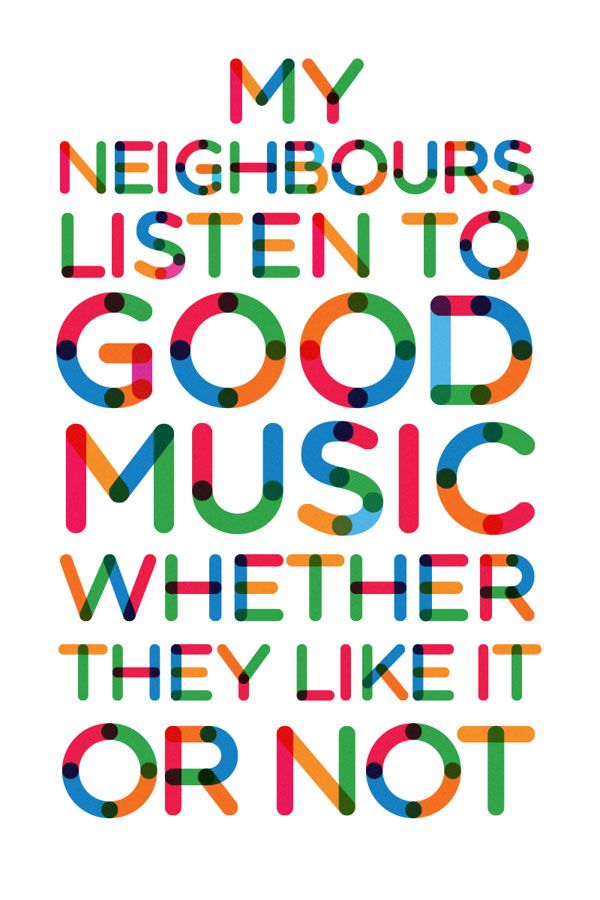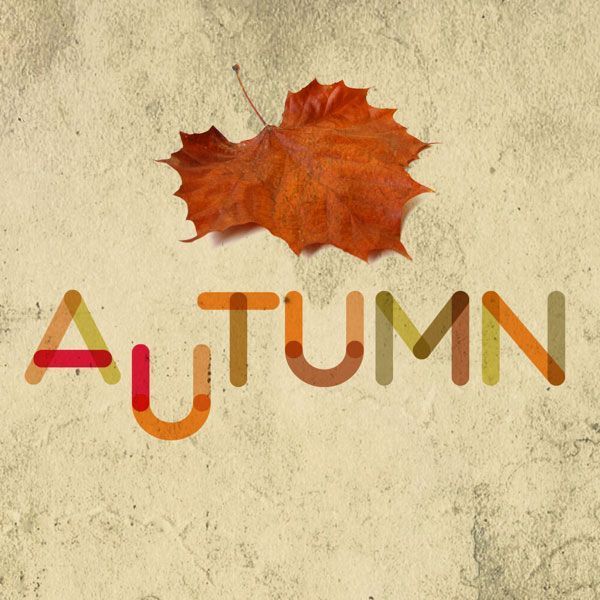
Fontfabric представляет бесплатный шрифт Multicolore. Уникальный округлый и, самое главное, разноцветный шрифт. Идеально подходит для создания как логотипов, так и графических работ. Источник вдохновения — логотип сайта.